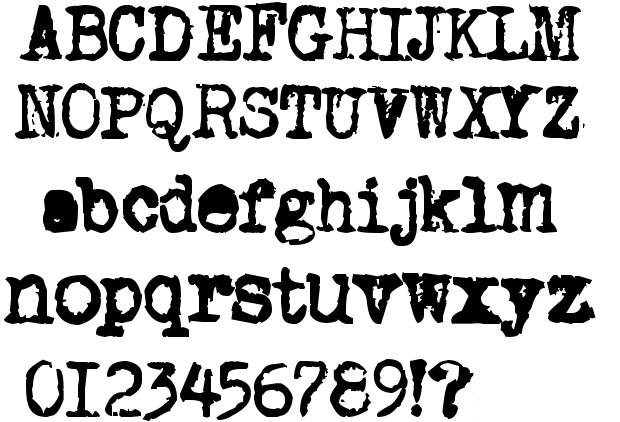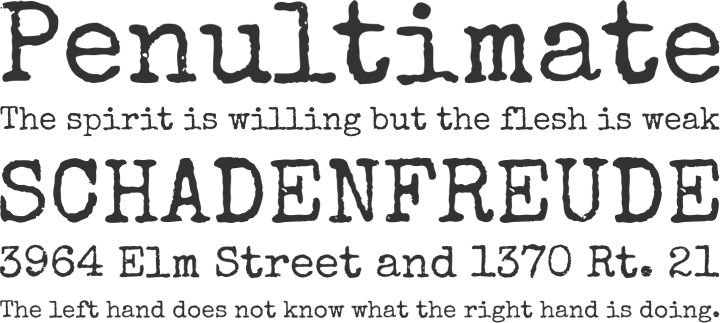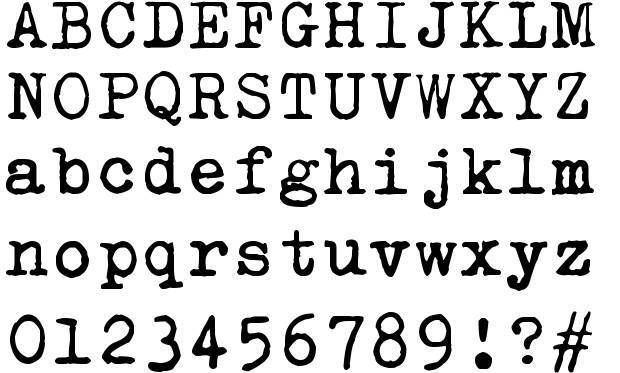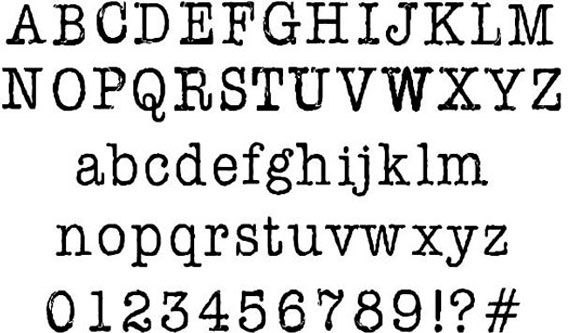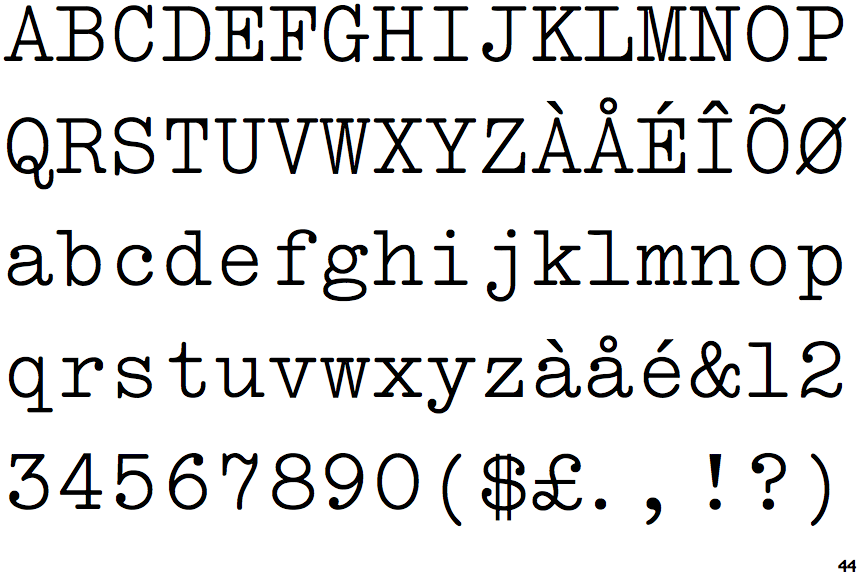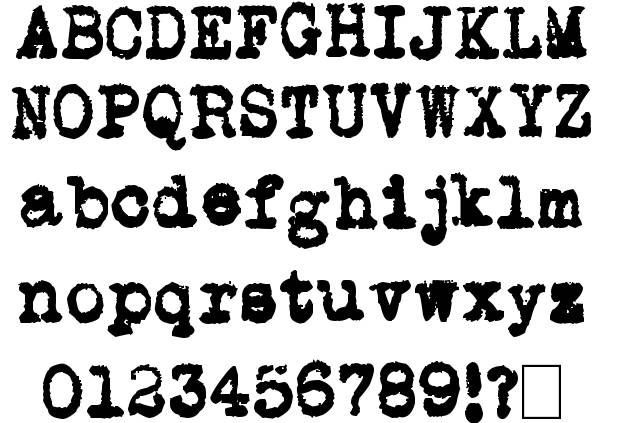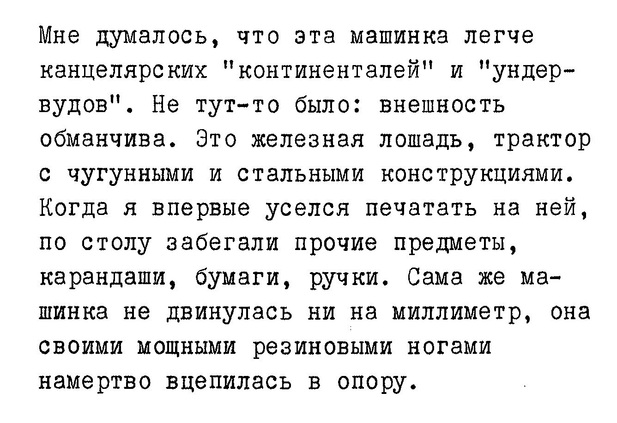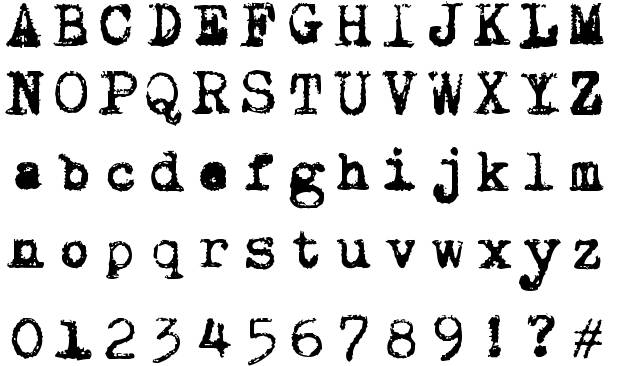
Шрифт печатной машинки: использование, названия, историческая справка
Винтажные шрифты, имитирующие печатную машинку, на сегодняшний день широко используются в веб-дизайне. Они придают тексту изящности и особого очарования, но применимы, конечно, не во всех случаях.
Историческая справка
До появления компьютерных систем для набора текста использовались печатные машинки. Они создавались в основном для переписывания ценных бумаг и рукописей. Шрифт печатной машинки не просто так неровный и немного расплывчатый. Когда один из первых изобретателей этого устройства, М. Алисов, презентовал свое детище, оно многим не понравилось, так как символы были эталонно ровными, как из типографии. Это создавало некоторые сложности при наборе документов, приходилось подвергать их цензуре. Остальные изобретатели учли эту ошибку, и шрифт печатной машинки стал таким, каким мы знаем его сейчас.
В печатных машинках используется так называемый моноширинный шрифт, который отличается одинаковой шириной символов.
Считается, что он менее удобный для чтения, чем пропорциональный шрифт, который используется в современной печати. Но и в наши дни он встречается в программировании при написании исходных кодов, этим шрифтом пишут киносценарии. Кстати, автомобильные номера тоже написаны моноширинным фонтом.
Для экономии пространства и уменьшения размеров устройства часто убирали многие клавиши. Например, цифры заменяли омографичными буквами, дефис и тире были одинаковыми, как и кавычки.
Использование
Большую часть ХХ века все официальные государственные документы были машинописными, издательства также требовали приносить напечатанные тексты, так как это сильно облегчало работу наборщиков.
В середине ХХ века, с появлением персональных компьютеров, печатные машинки ушли в прошлое. Но шрифт печатной машинки до сих пор активно используется дизайнерами. Он отлично смотрится во многих стилях, придает эффект винтажности. Создается впечатление работы рукотворной, а не выполненной бездушной машиной.
Как называется шрифт печатной машинки?
В настоящее время есть более 15-ти их разновидностей для Photoshop. Каждый шрифт печатной машинки для «Фотошопа» имитирует либо стиль определенного устройства, либо написание в разных изданиях (газеты, типография). Многие стили доступны как в кириллице, так и в латинице. Наиболее похожим выглядит фонт B52 с его большим расстоянием между символами и эффектом потертости. Есть и другие шрифты, например:
- DS Moster имеет довольно интересный эффект, при котором некоторые символы пропечатываются жирнее. И буквы располагаются не ровно в строке, а «пляшут», делая текст очень реалистичным.
- Underwood полностью копирует стиль написания одноименной машинки.
- Harting и 1942 Report выглядят очень потертыми, как будто краска в машинке начинает заканчиваться.
- Junkos Typewriter сильно стилизован, буквы в нем разного размера и неровные, много «пятен от чернил».
- Type Writer, Type wrong и King больше приближены к компьютерному или типографскому набору, они четкие, ровные и без мелких пятен.
- Old Newspaper похож на стиль печати в газетах в начале ХХ века.
На сегодняшний день мы имеем огромное количество возможностей. Шрифты используются практически везде, от государственных документов до рекламы и искусства. Шрифт печатной машинки придаст эффект старины любому сайту или изображению.
Если у вас есть печатная машинка, хорошо бы знать, каким шрифтом она печатает. Я предлагаю поговорить о машинописной шрифтологии.Типографисты, описывая шрифты и их «поведение» в тексте, обычно выражаются сложными терминами: «кегль», «шпация», «интерлиньяж», «апроши», «полуапроши», а когда они говорят о размерах шрифта, они сообщают о неких пунктах, математическое значение которых, кажется, понятно только избранным.Мне очень нравится типографика, шрифты и прочие вещи, с ними связанные. Понимаю, что наука эта со своими секретами и тонкостями, но в рамках темы пишущих машинок я бы хотел поговорить об этом на понятном человеческом языке.
Для начала подчеркнём одну очень важную вещь: машинописные шрифты коренным образом отличаются от типографских, так что и принцип их измерения соответствующий.(Типографские шрифты, материалы и принадлежности. Союзполиграфпром. М., 1950.) В прежние докомпьютерные времена полоса набора (часть страницы, отведённая под текст) складывалась из отдельных литер — металлических брусочков с зеркальными формами букв и других символов. Отсылка к металлическому набору может показаться устаревшей, но на самом деле современные дизайнеры и верстальщики до сих пор, часто сами того не осознавая, мыслят теми же категориями брусковых литер. Составление печатной формы при помощи набора брусковых литер
University Creative Services Photography Металлический набор не только определил многие особенности современных шрифтов, но и продолжает влиять на процесс их разработки и применения.
Дело не только в традиции. За столетия развития книгопечатания правила и принципы оформления текстов довели до совершенства, если теперь и можно выдумать что-то новое, это скорее будет претендовать на уровень «фишки», но никак на гениальность. Типографская форма LTS Rare Базовым понятием в типографском шрифте является кегль – размер высоты буквы или знака, включая нижние и верхние выносные элементы и заплечики.Заплечики – невидимая область, но они со времён металлического набора влияют на размер знака по сию пору. При ручном наборе благодаря этим заплечикам создавался минимальный интерлиньяж — междустрочное расстояние (чтобы увеличить интерлиньяж использовался шпон — специальный пробельный материал, пластина).
JMH Typewriter by Jorge Morón
Этот шрифт предлагает эстетику традиционного шрифта для пишущих машинок с его дизайном с засечками и неровными линиями на символах для эффекта свежести чернил.